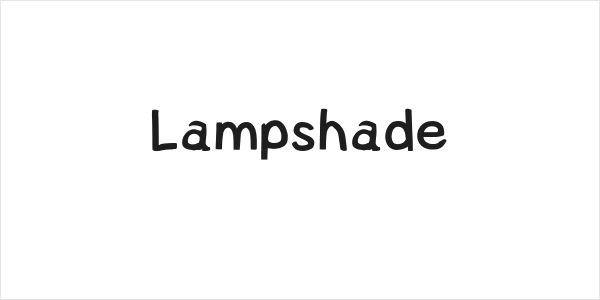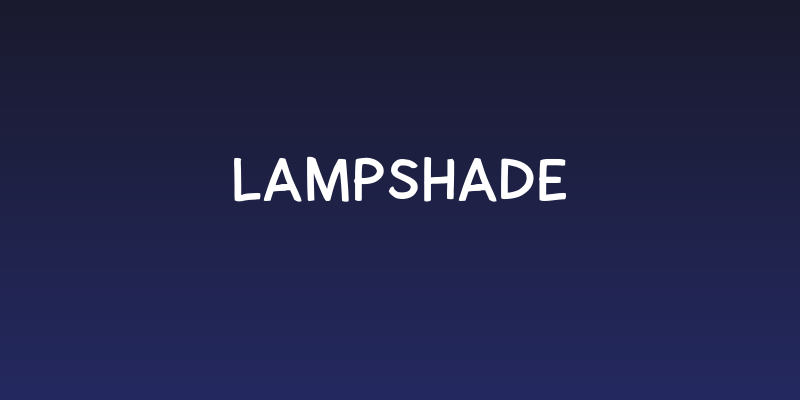
Lampshade Font
| Estilo general | Playful |
| Proyectos propuestos | Ideal for children's books, playful branding, casual invitations, and creative posters. |